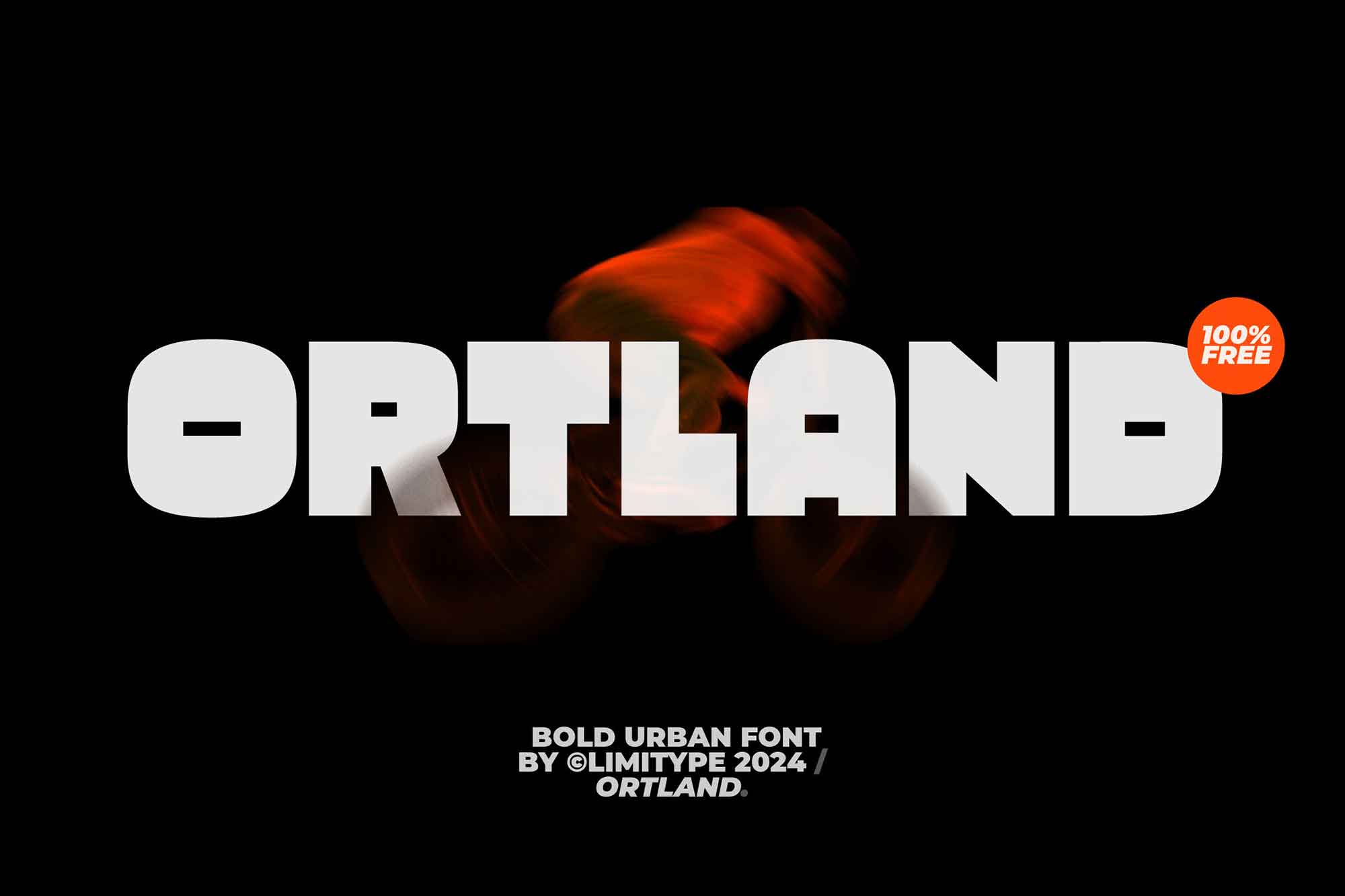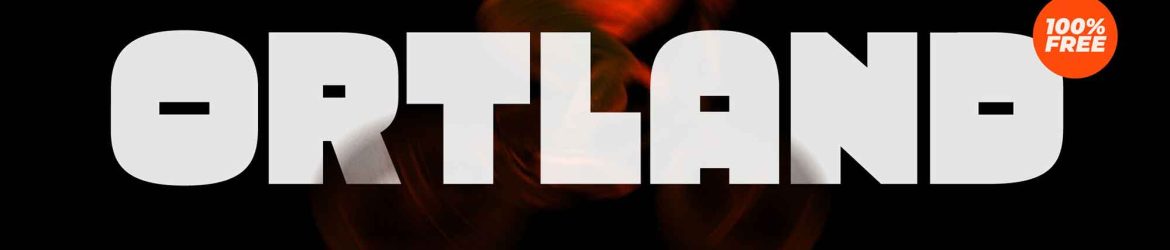
Ortland Display Font – Download Grátis
Ortland é uma fonte de display pesada com letras brilhantes e um estilo urbano. Esta nova tipografia da Limitype está disponível de graça, permitindo-lhe usar-a tanto para trabalho comercial quanto pessoal. Ortland é ideal para cabeçalhos ou títulos em postais, placas de propaganda, capas de revistas ou paredes de lojas. A fonte é multilíngue, e acompanha caracteres minúsculos, maiúsculos e números. Este recurso gráfico é uma ótima opção para designers que buscam uma fonte robusta e sofisticada para incorporar em seus projetos.